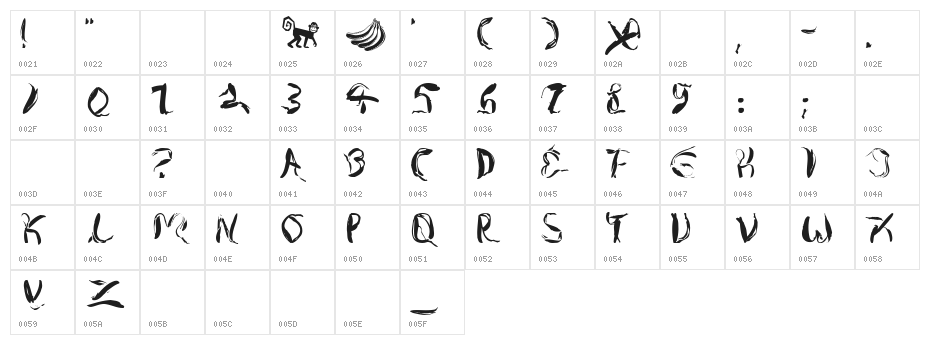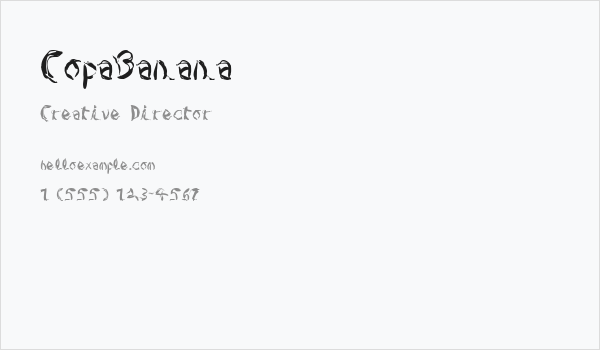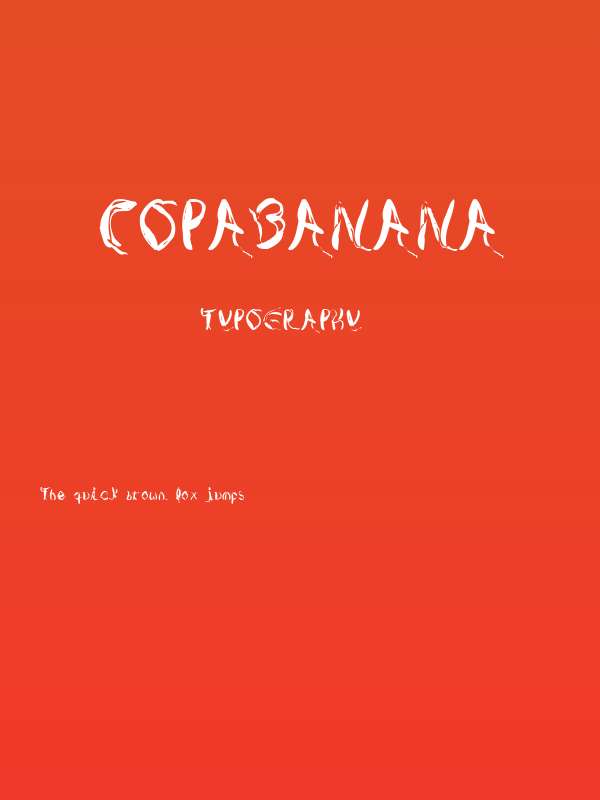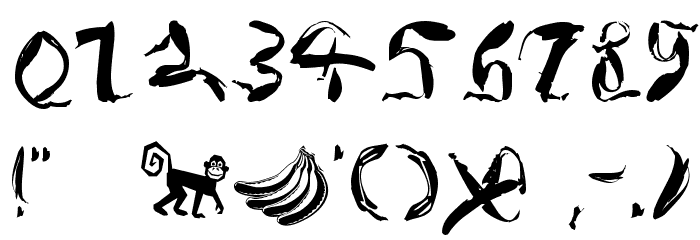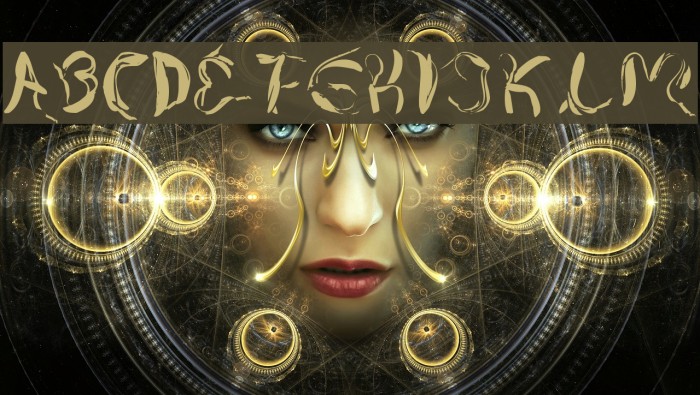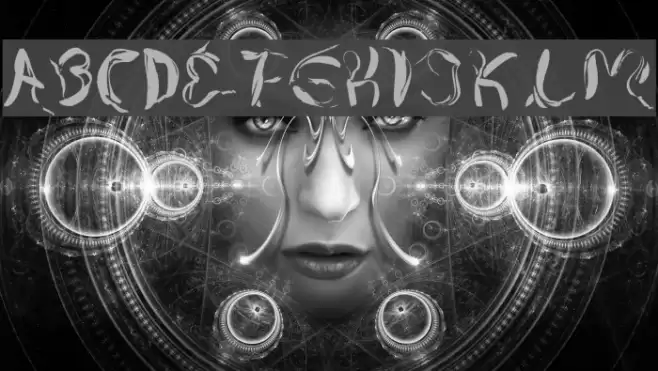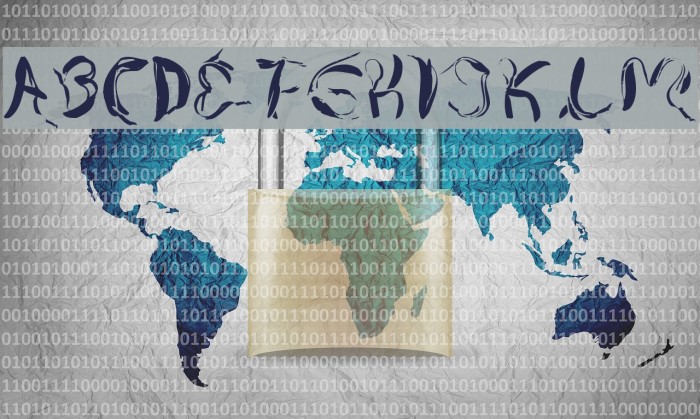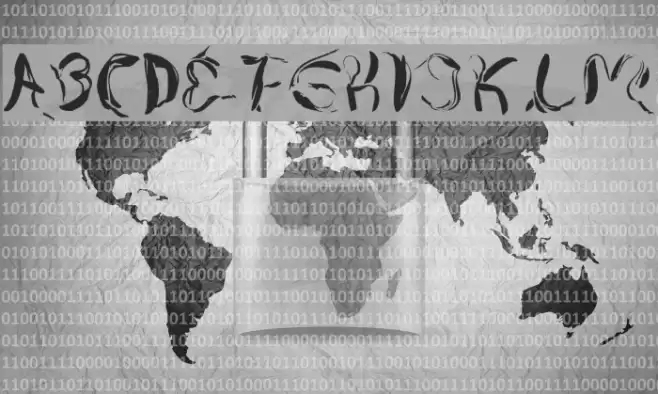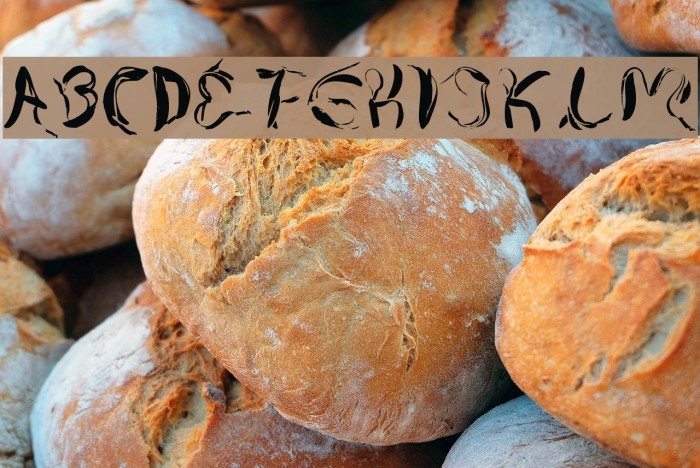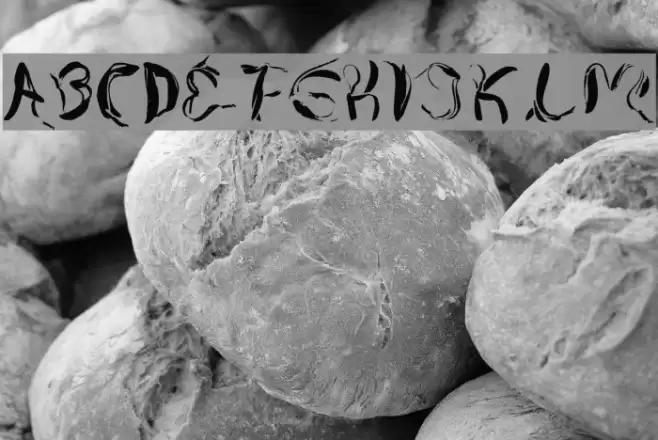
CopaBanana Font
| Stil general | Artistic, Playful |
| Caz de utilizare | Logos, Posters, Creative projects |
| Proiecte propuse | Ideal for creative projects such as children's book covers, playful branding, artistic posters, and event invitations. |